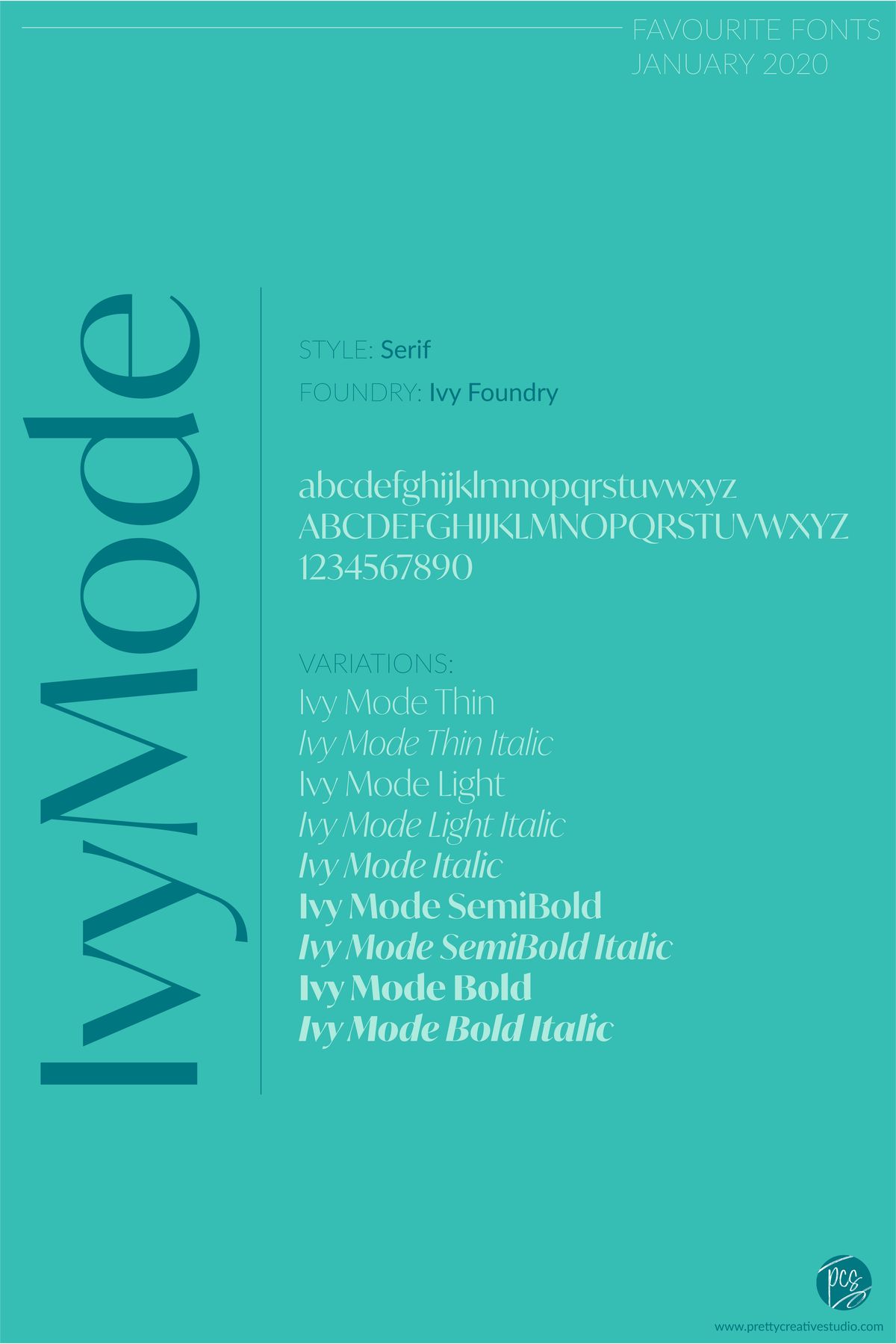
Designer thường gặp rắc rối khi dùng font IvyMode bị lỗi hiển thị các ký tự “đ, ơ, ư” hoặc file bị vỡ hạt khi in logo lên hộp quà sang trọng. Điều này làm giảm giá trị của các nhãn hàng thời trang, mỹ phẩm cao cấp. Xưởng In Viva cung cấp bộ font IvyMode việt hóa free trọn bộ, đảm bảo đường nét thanh mảnh, sắc nét phục vụ cho nhu cầu thiết kế và sản xuất bao bì đẳng cấp.
Font IvyMode là gì?
IvyMode là một bộ phông chữ thuộc dòng Sans-serif nhưng mang hơi hướng của các thiết kế Serif cổ điển với các nét thanh nét đậm cực kỳ tinh tế. Đây là tuyệt phẩm dành cho ngành công nghệ cao, thời trang xa xỉ và thiết kế tạp chí sang trọng. Font IvyMode gây ấn tượng bởi sự tương phản mạnh mẽ giữa các nét, tạo nên một vẻ ngoài vừa hiện đại vừa quý tộc, giúp nâng tầm mọi bản thiết kế.
Tuy nhiên, do cấu trúc nét rất mảnh ở một số vị trí, IvyMode đòi hỏi sự cẩn trọng rất lớn trong việc hiển thị và in ấn. Bản font IvyMode việt hóa được chúng tôi chia sẻ đã được xử lý hoàn hảo để các dấu tiếng Việt không làm mất đi vẻ đẹp thanh thoát của bộ chữ gốc, giúp bạn yên tâm sử dụng cho các dự án nhận diện thương hiệu tại Việt Nam.
Lưu ý: Vì font IvyMode có những nét cực mảnh, khi thiết kế cho in ấn lên các chất liệu nhám như giấy Kraft, bạn nên tăng nhẹ độ dày viền (Stroke) để chữ không bị mất nét do mực thấm vào sợi giấy.
1. Font IvyMode việt hóa này có hỗ trợ đầy đủ các ký tự đặc biệt không?
Bản việt hóa tại In Viva hỗ trợ trọn bộ 89 ký tự tiếng Việt và các ký tự đặc biệt, đảm bảo không bị lỗi dấu khi gõ văn bản dài.
2. Tôi có thể in chữ cực nhỏ dùng font IvyMode lên tem nhãn không?
Chúng tôi khuyên dùng font IvyMode cho tiêu đề hoặc logo. Với các dòng chữ cực nhỏ trên tem nhãn, bạn nên chọn các biến thể có nét dày hơn để đảm bảo độ rõ nét.